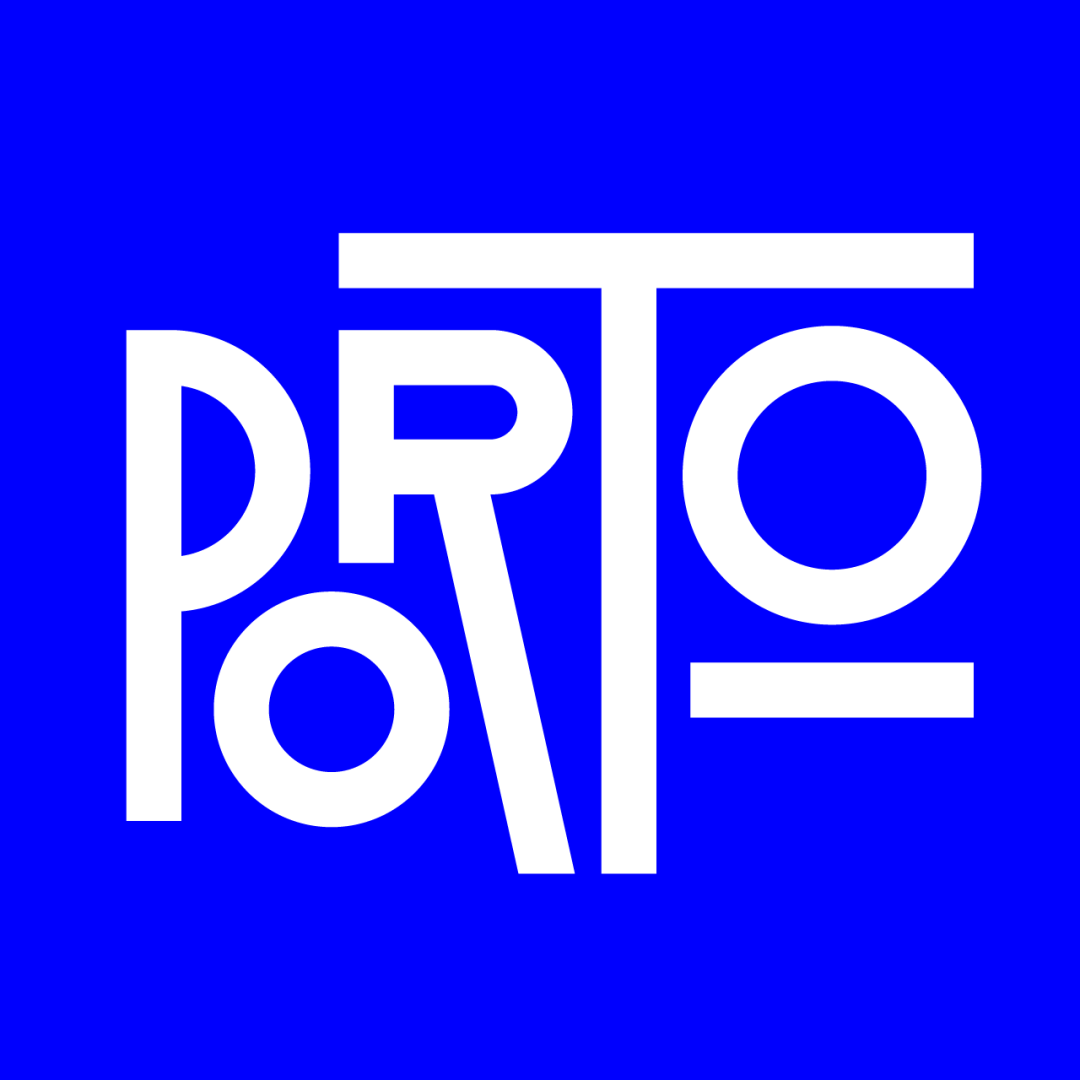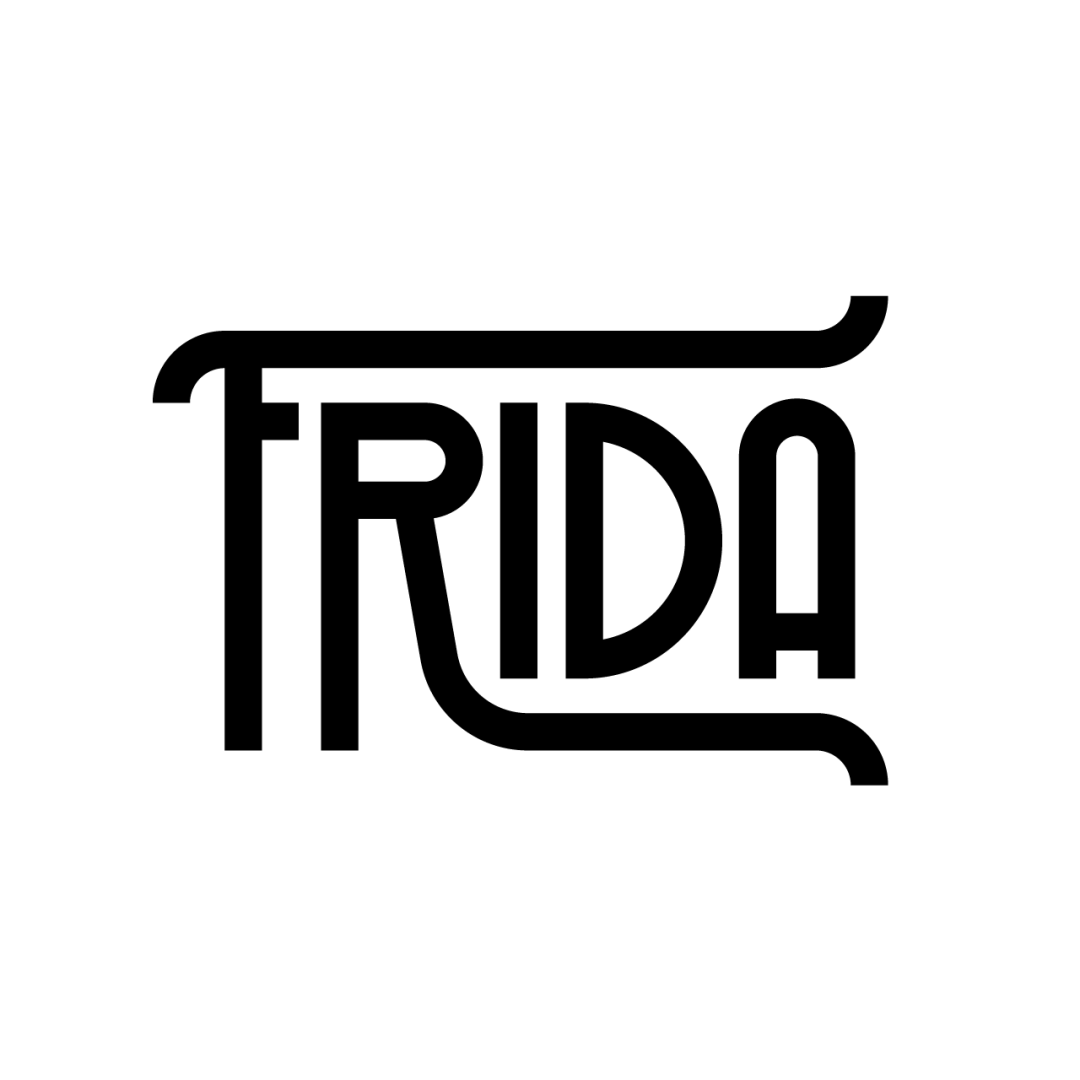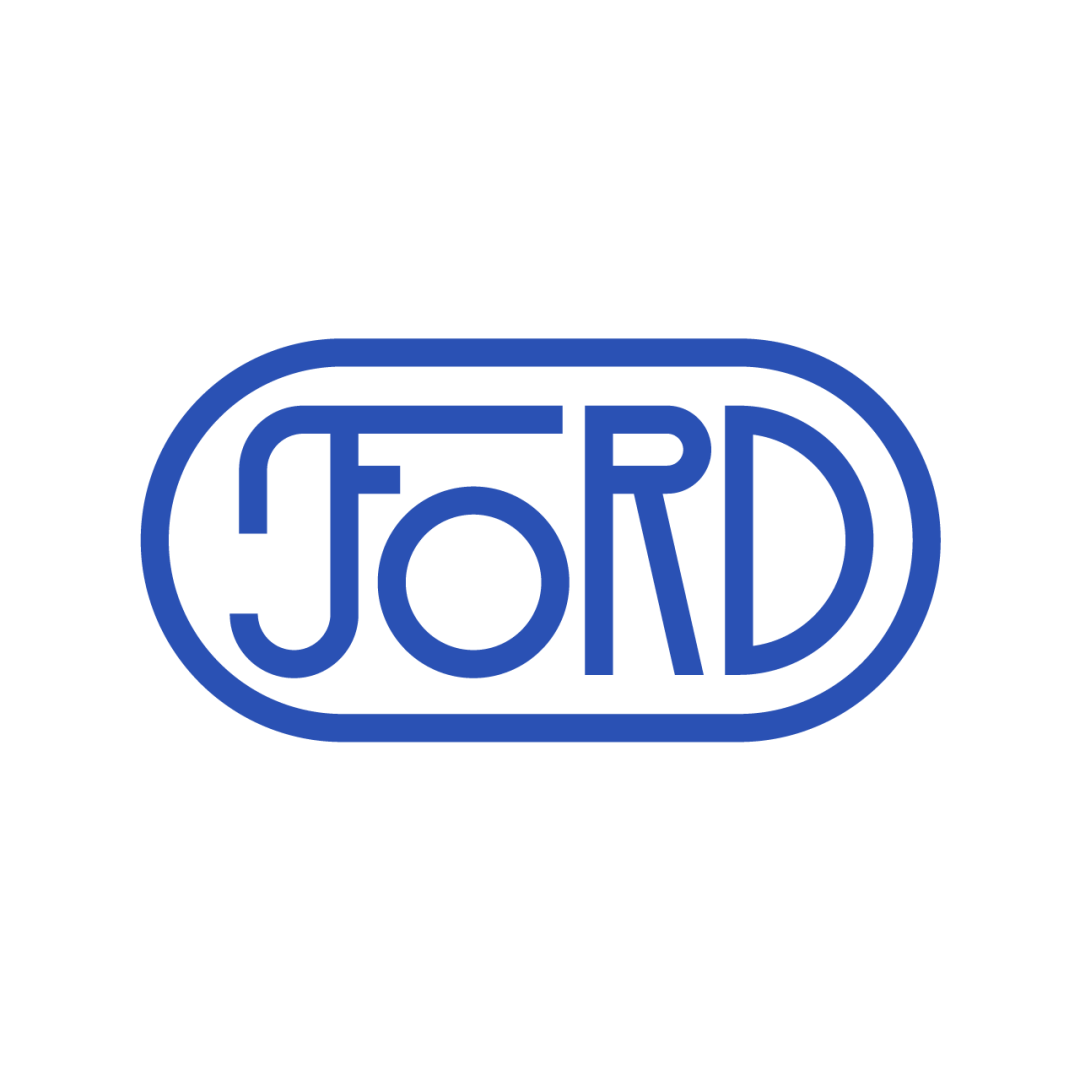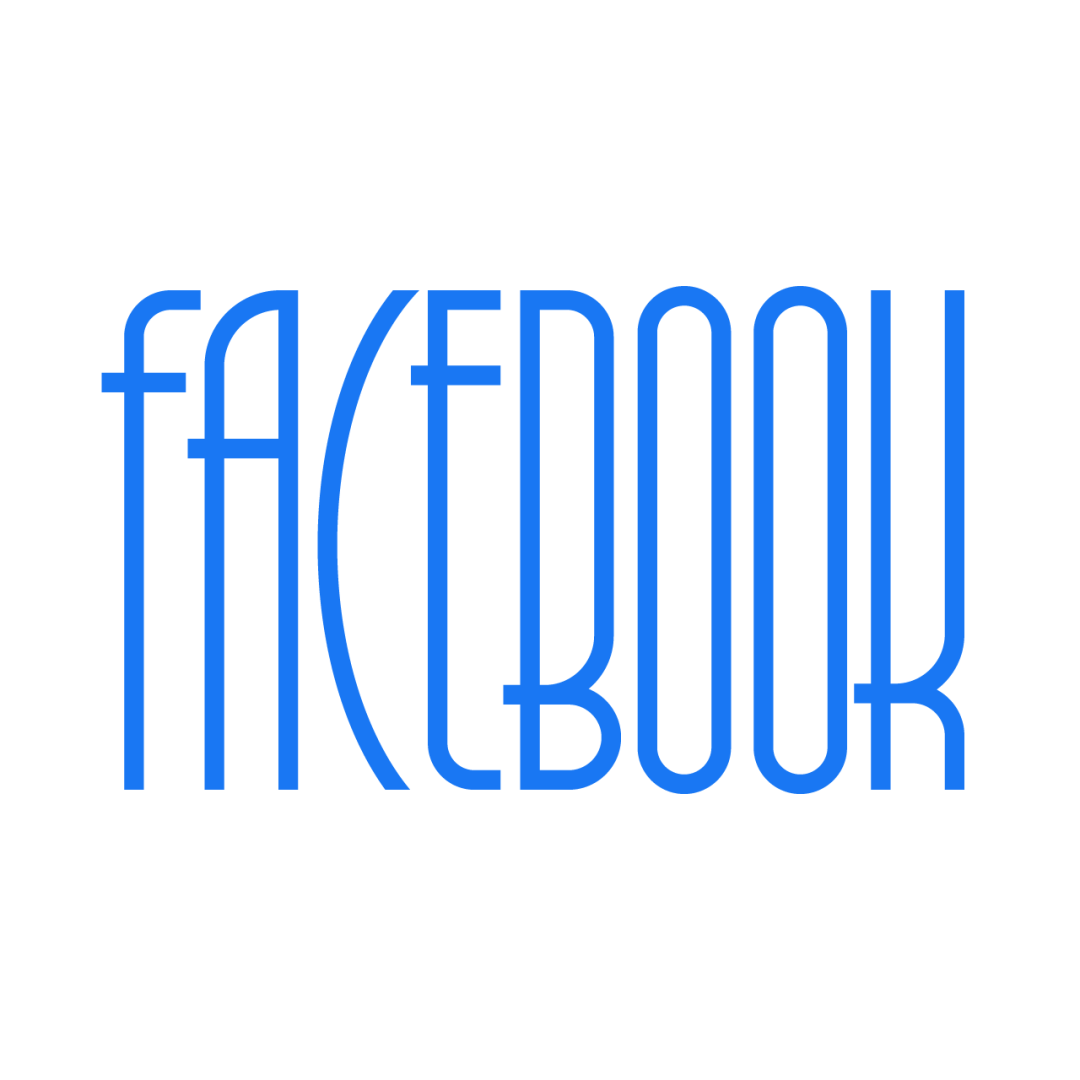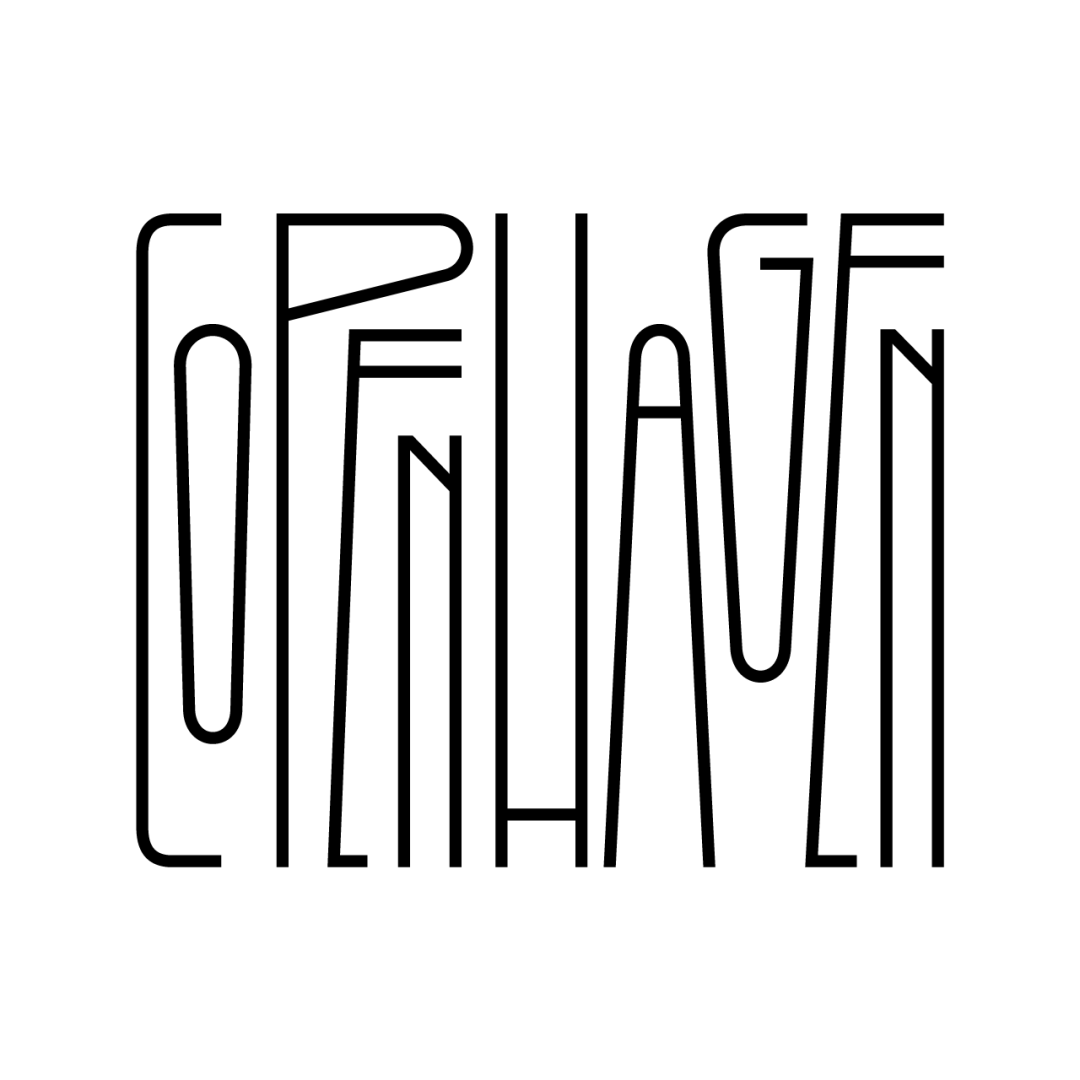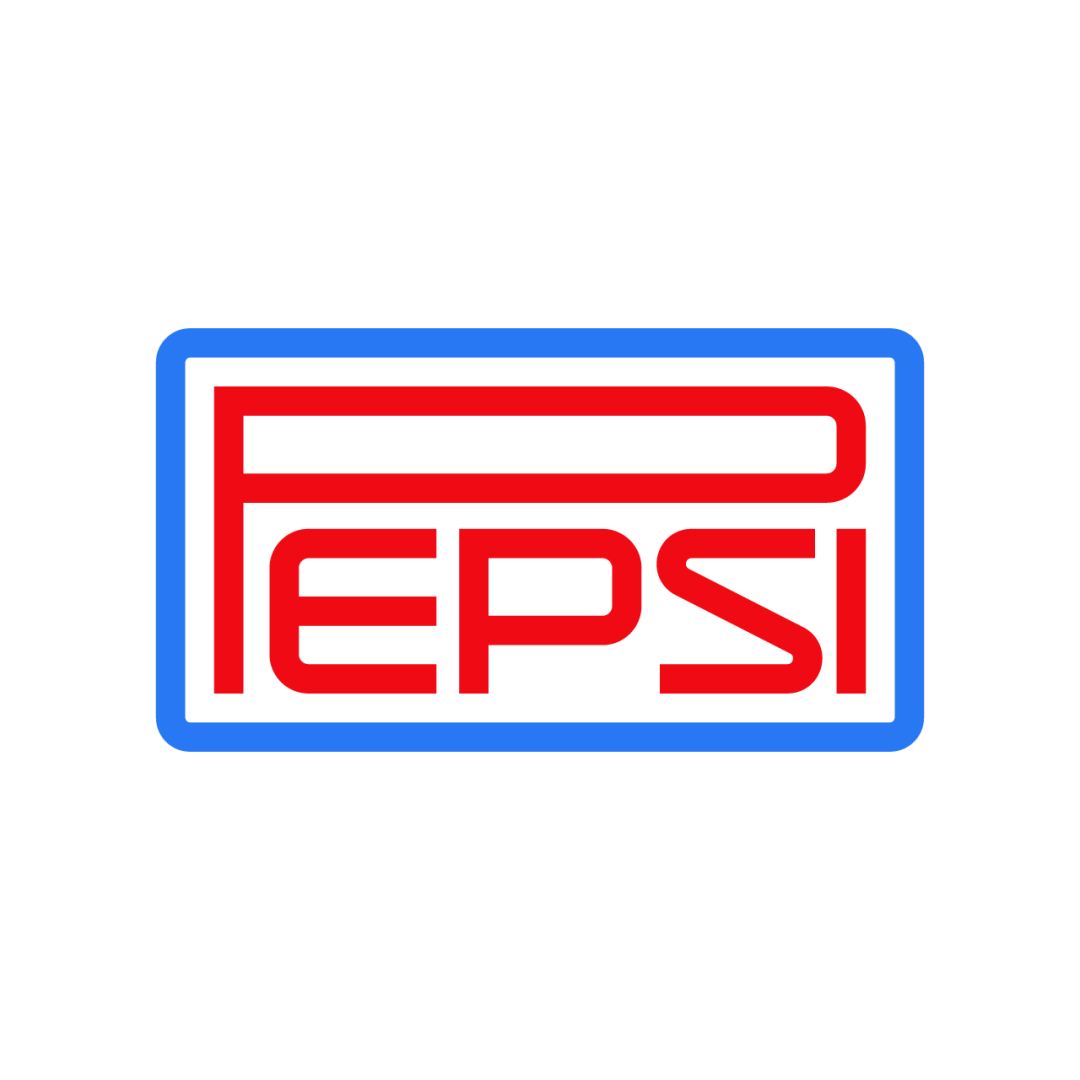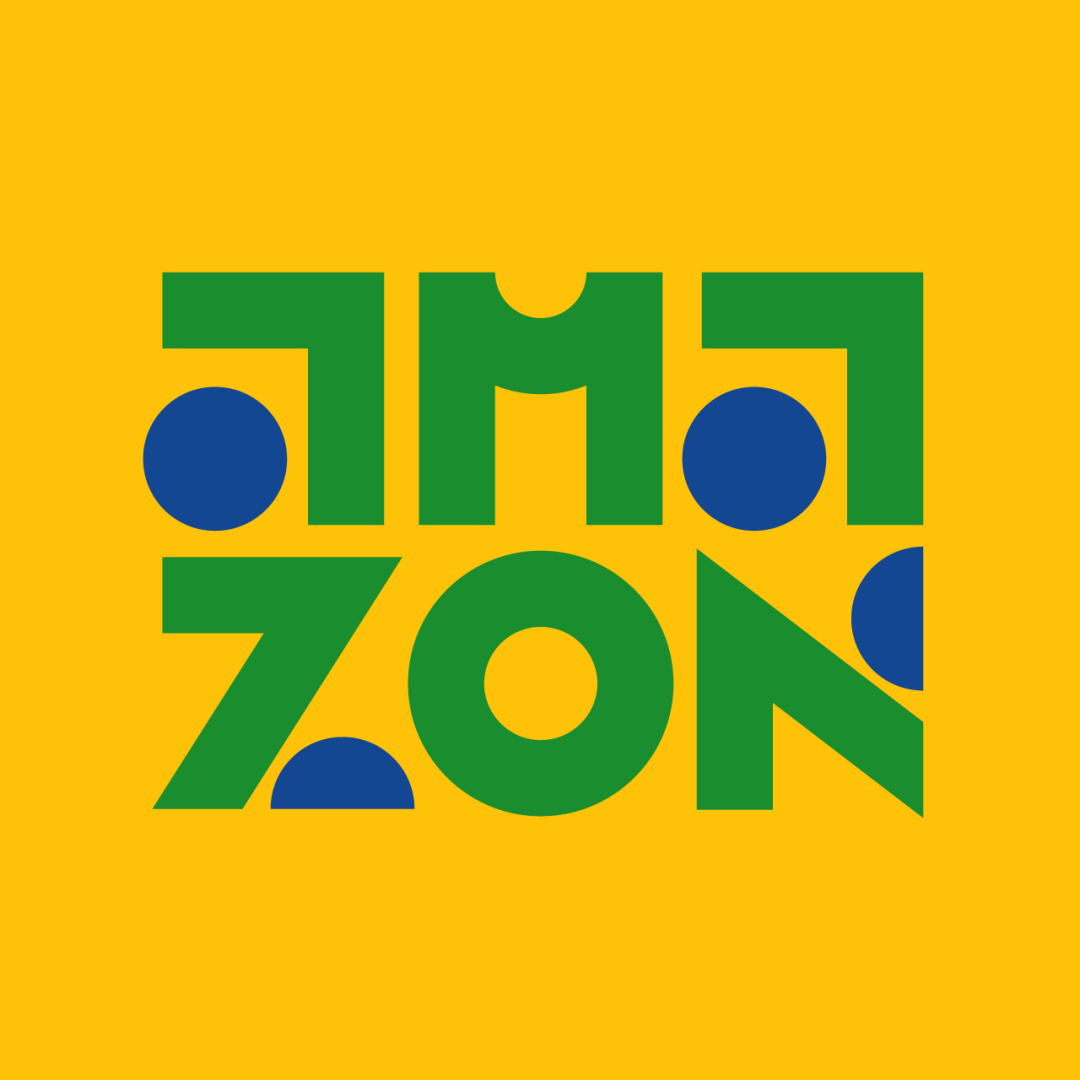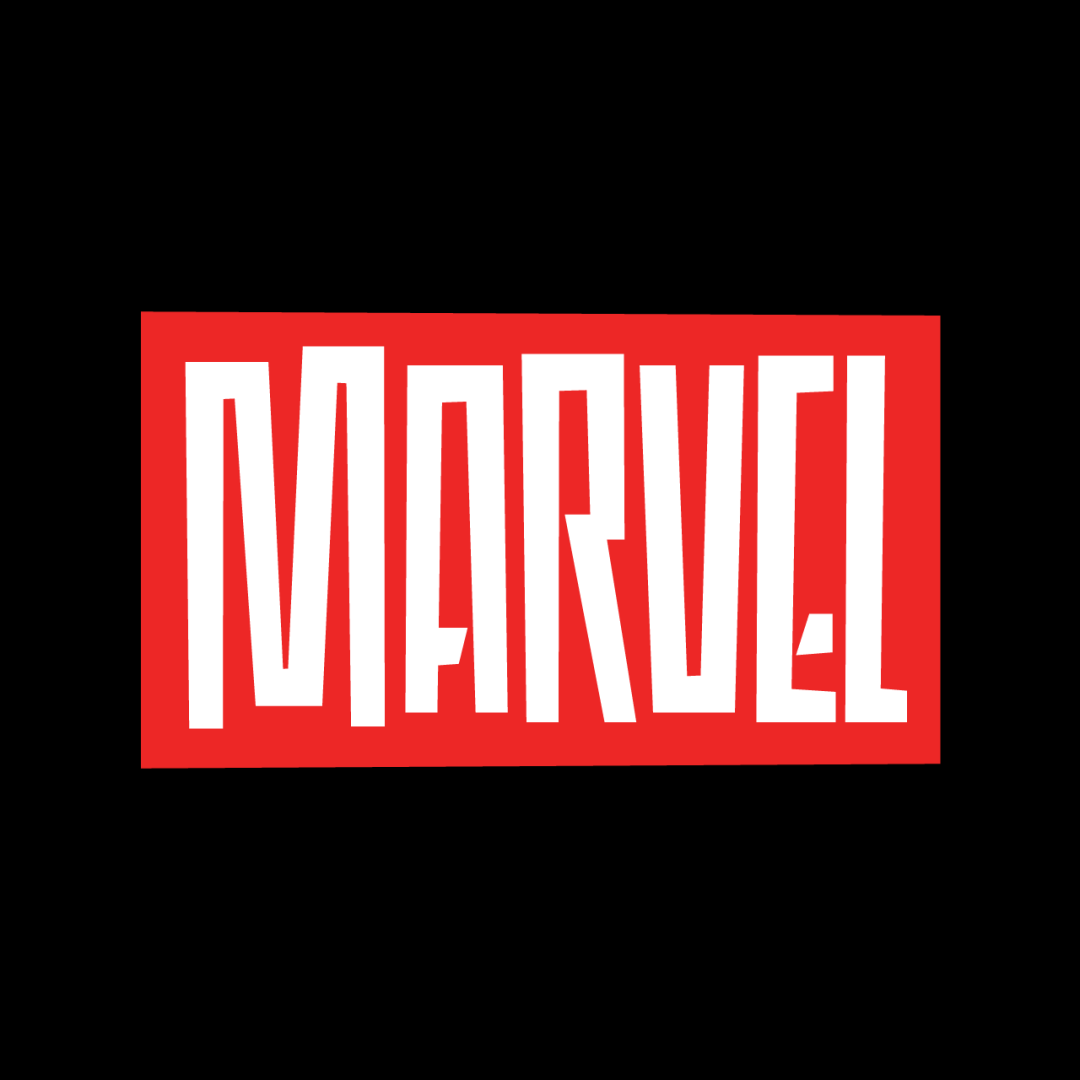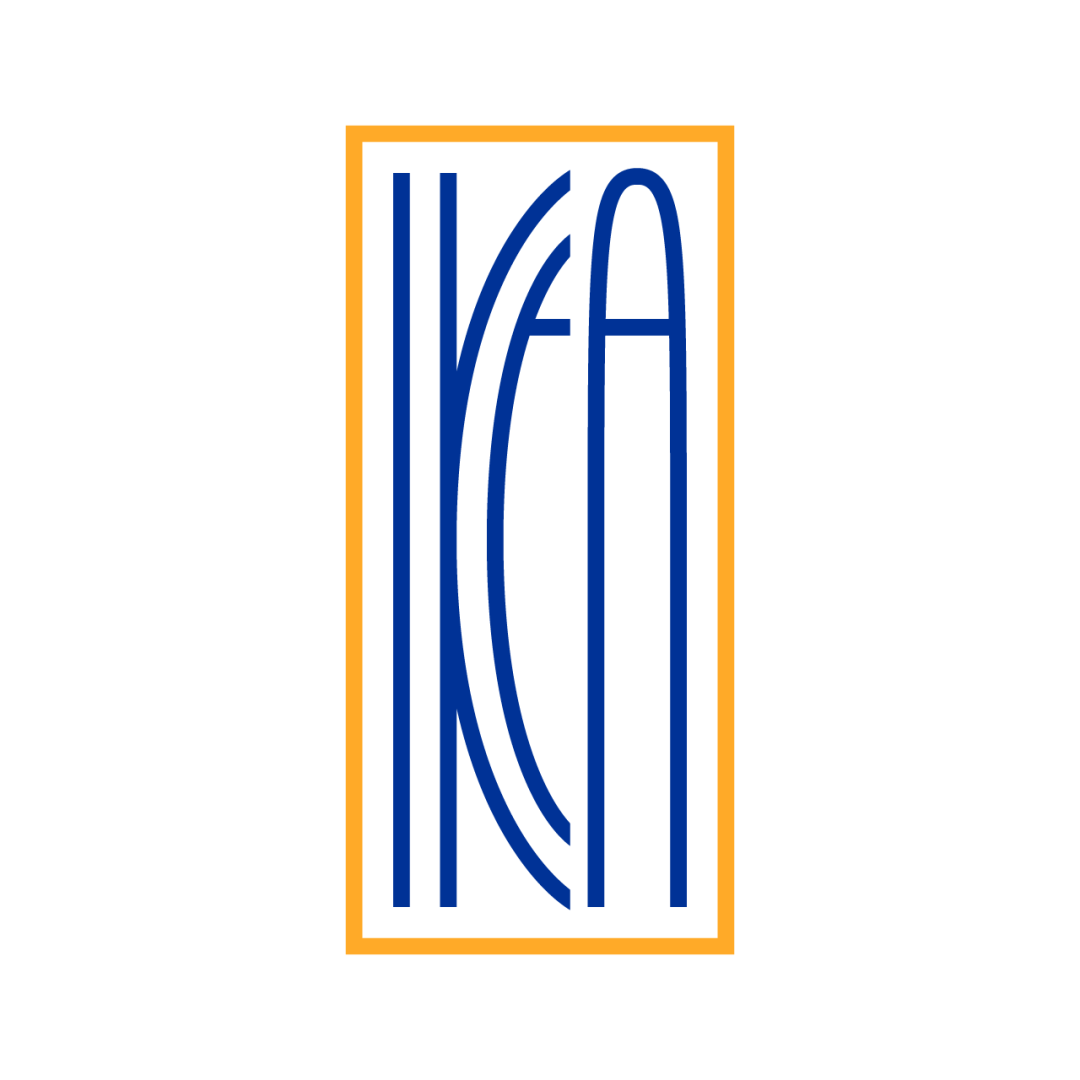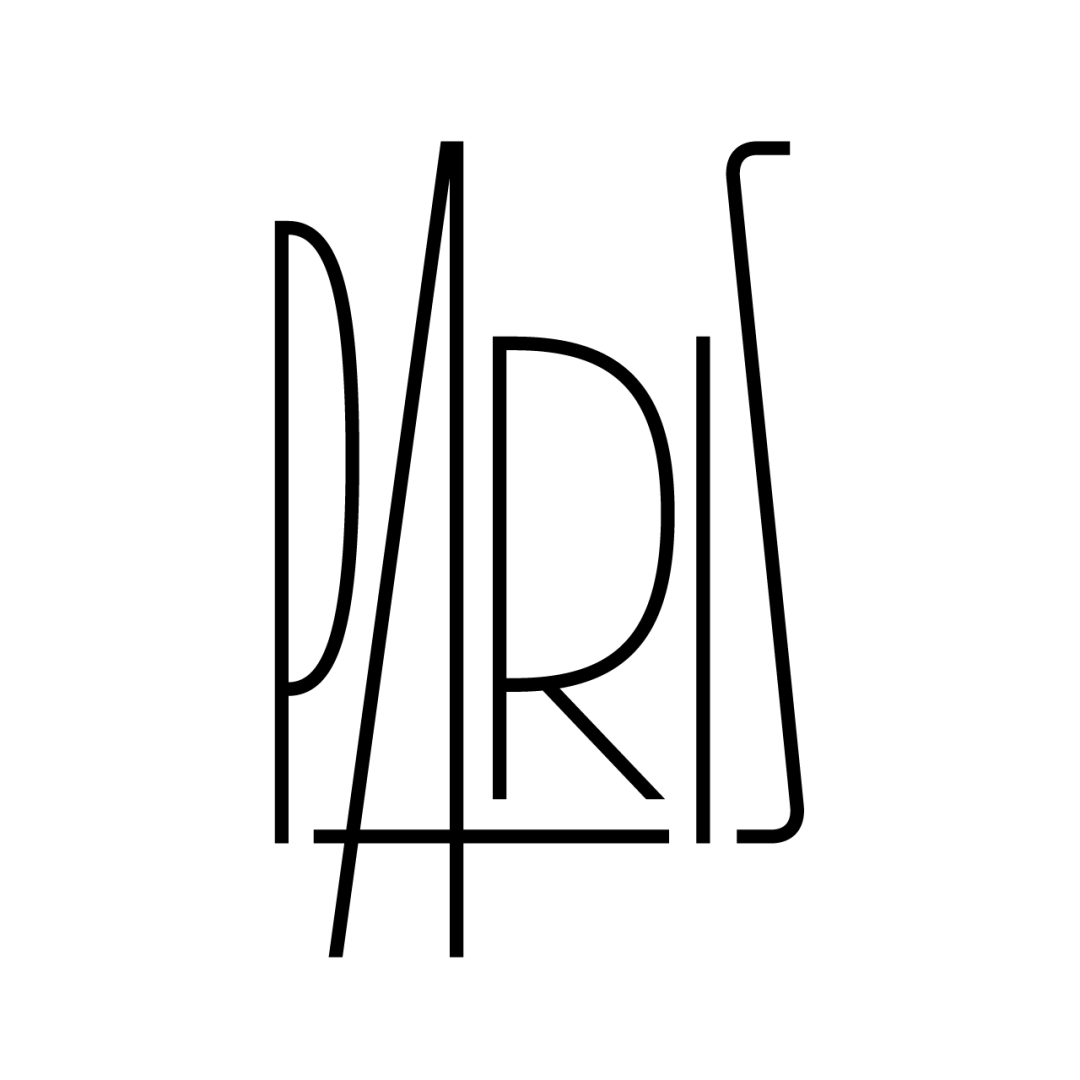
文字排版设计的创造性和趣味性分享
葡萄牙字体设计师 Rafael Serra,喜欢玩耍字体,他的文字排版设计非常有创造性和趣味性,一起来看这些实验作品。
01
字母系列X
02
字母系列XI
03
字母系列XII
04
字母系列IX
05
字母系列V
06
字母系列VI
07
字母系列VII
08
字母系列VIII
09
字母系列IV
10
字母系列I
11
字母系列II
12
字母系列III
13
LOGO系列I
14
LOGO系列II
15
LOGO系列III
16
LOGO系列IV
17
Antiga 字体
18
Silas类型
Rafael Serra的作品简洁又充满创意性
而且Rafael Serra 善于运用强烈的色彩对比。